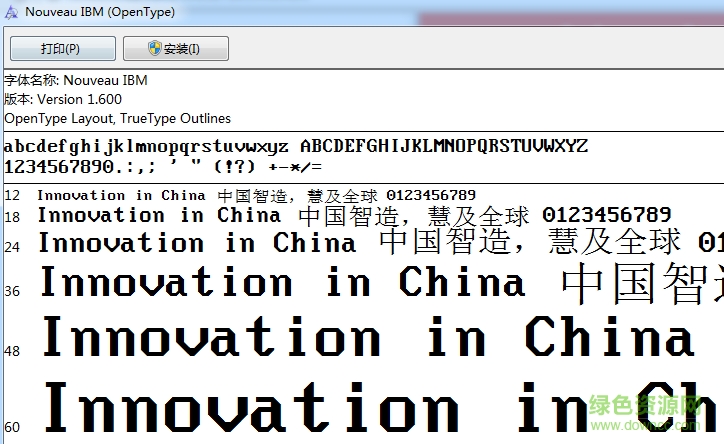
IBM標志字體
IBM字體是一款非常具有個性的英文字體,這款字體為用戶提供了以個性鮮明的字跡,讓得許多朋友能夠從這里找到屬于你的style,歡迎來綠色資源網(wǎng)下載使用!
IBM字體是一款個性英文字體,該字體能夠讓用戶快速的彰顯出自己的個性,表現(xiàn)不凡。有需要的朋友就趕快來綠色資源網(wǎng)下載吧!